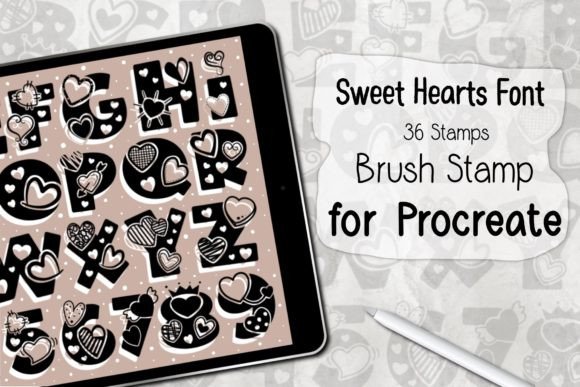
Sweet Hearts Font Procreate Stamp
Att hitta rätt designelement kan vara utmanande, men Sweet Hearts Font Procreate Stamp erbjuder en exceptionell samling som omedelbart lyfter ditt arbete.